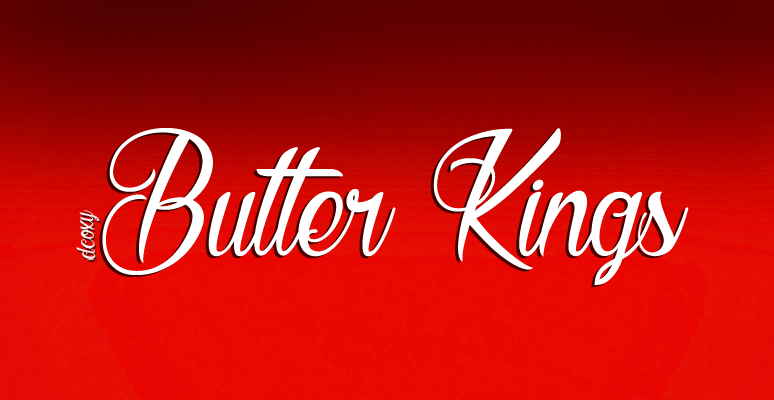
A “Butter Kings” é uma fonte ideal para quem busca uma mão-dupla moderna e elegante para trabalhos artísticos, design editorial ou aplicativos web. O designer Hamilton criou esta font com estilo chamado calligrafia, oferecendo você um recurso de alta qualidade sem custos extras para uso pessoal. Esta font é perfeita para projetos que exigem a transição entre linhas diretas e curvas suaves, proporcionando uma variedade de opções de tipografia para os mais variados cenários. Para qualquer aplicação comercial ou promocional, um licenciamento é necessário, então fique à vontade para entrar em contato antes:  Estamos ansiosos para ver como a “Butter Kings” irá moldar seus projetos!